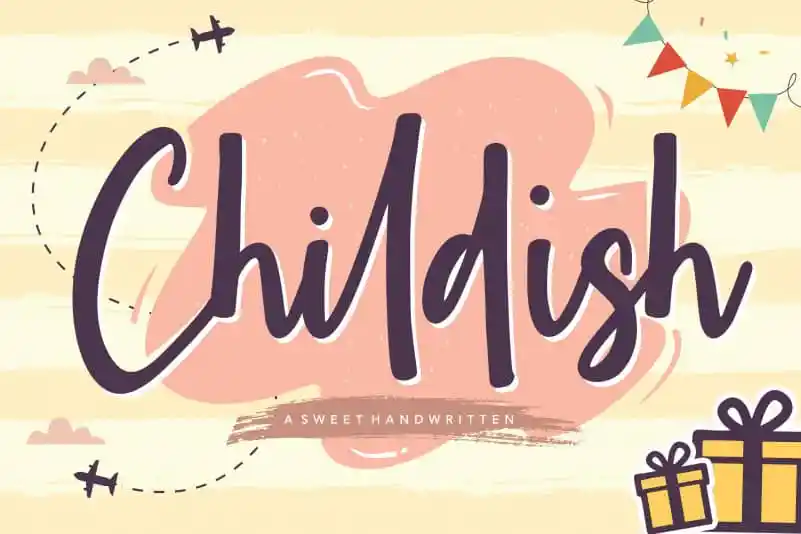
Childish Sweet Handwritten Font – Download Grátis
A Childish Sweet Handwritten Font é uma escolha excepcional para projetos que desejam transmitir um toque delicado e leve, sem perder a elegância. Seu traçado suave e bem definido faz dele perfeito para diversos aplicativos, como embalagens de produtos, projetos de marca, revistas, mídias sociais, casamentos ou simplesmente para destacar frases em um fundo. Este fonte é o ideal para expressar a simplicidade e a delicadeza numa variedade de cenários gráficos. Com seu estilo encantador e despojado, a Childish Sweet Handwritten Font será uma ótima adição à sua coleção de recursos gráficos.